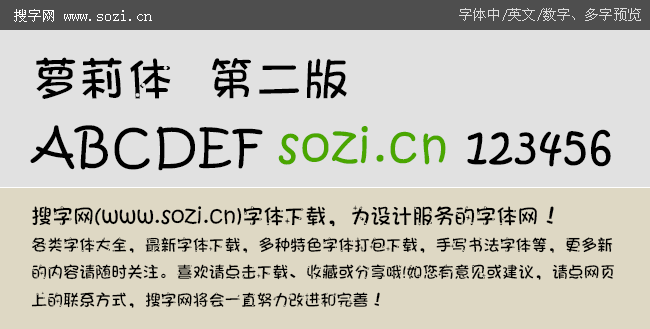
蘿莉體 第二版
搜字網(wǎng)提供一款蘿莉體 第二版中文字體下載,蘿莉體是一款俏皮可愛的卡通字體,字形可愛,字間又添加了可愛的卡通圖案點(diǎn)綴,非常有趣,適合應(yīng)用于POP設(shè)計(jì)、兒童包裝設(shè)計(jì)、卡通圖案設(shè)計(jì)等應(yīng)用。